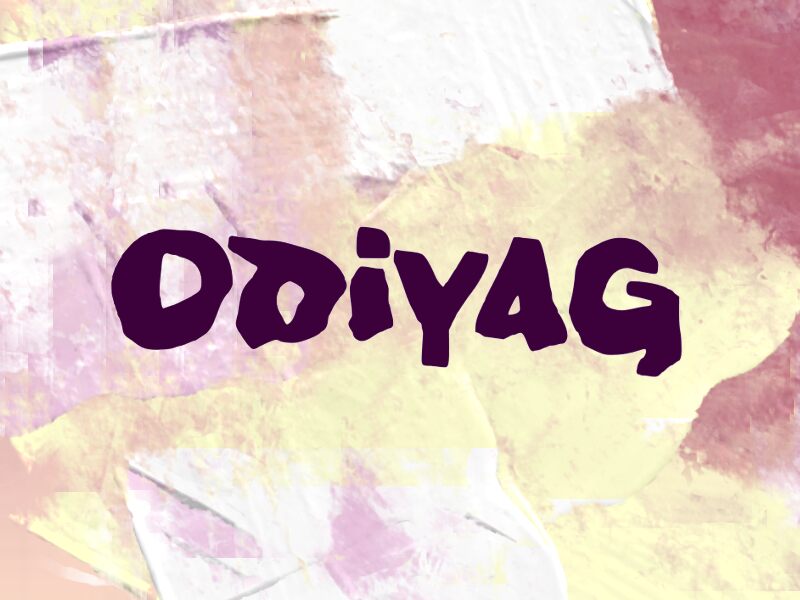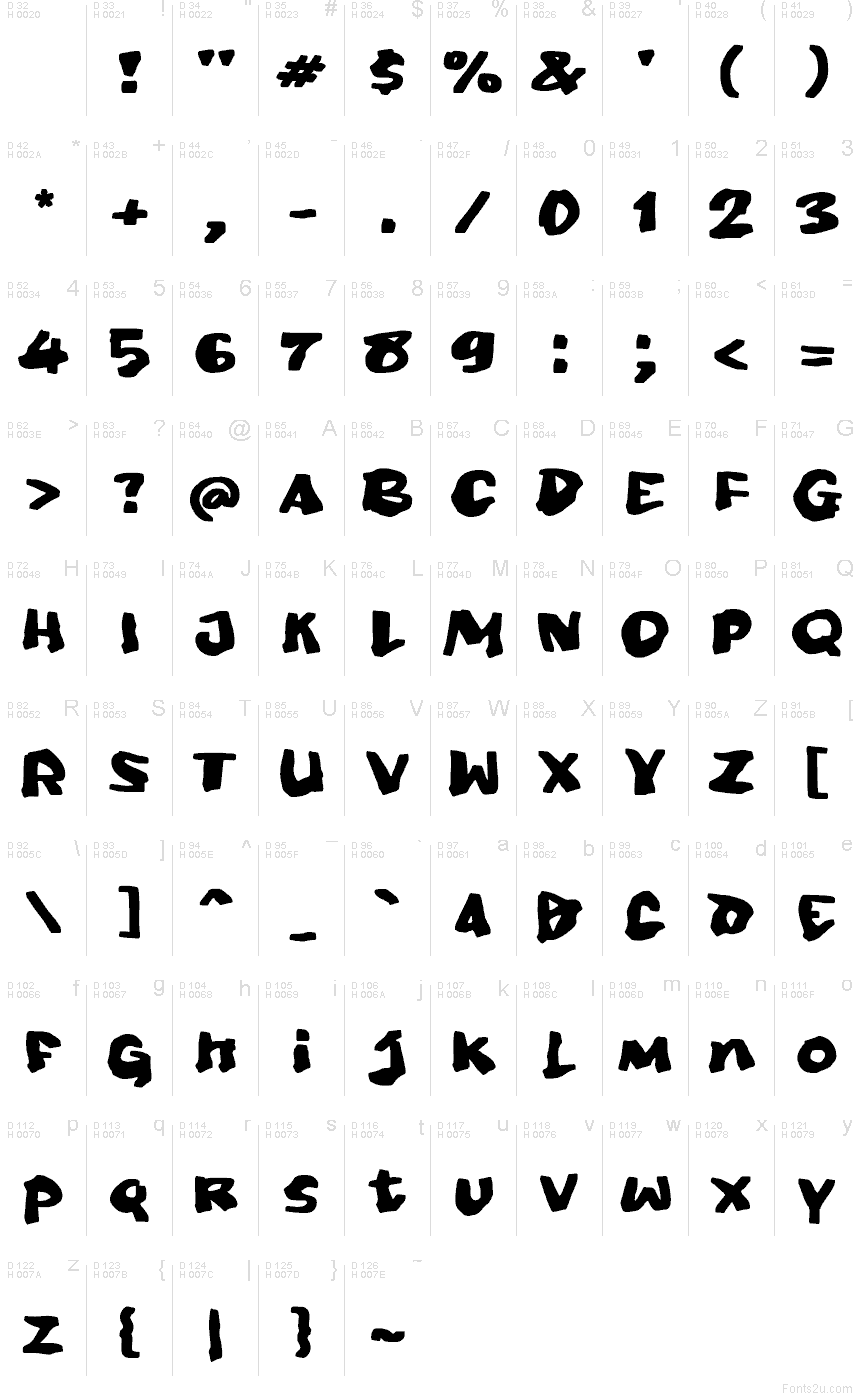
Odiyag
Odiyag je bezplatné písmo v štýle graffiti od Wep, ktoré využíva vypuklé, akoby ručne vyrezávané siluety, čo pôsobí skôr ako maľované škvrny než ako úhľadné písmená kreslené fixkou. Tento surový, nepravidelný rytmus dodáva dizajnu charakter pouličných tagov, zatiaľ čo hlboké výrezy vo vnútri znakov zabezpečujú, aby tvary nepôsobili ako zliate bloky.
Plagáty, hudobné letáky, skate grafika, nálepky a výrazné nadpisy na sociálnych sieťach sú pre toto písmo ideálne, najmä ak hľadáte surový, domácky vzhľad namiesto precíznosti spreja. Najlepšie vynikne v krátkych nadpisoch a logotypoch, pretože jeho nepravidelné obrysy vytvárajú silný vizuálny vzor, ktorý funguje lepšie než dlhý, rovnomerný text.